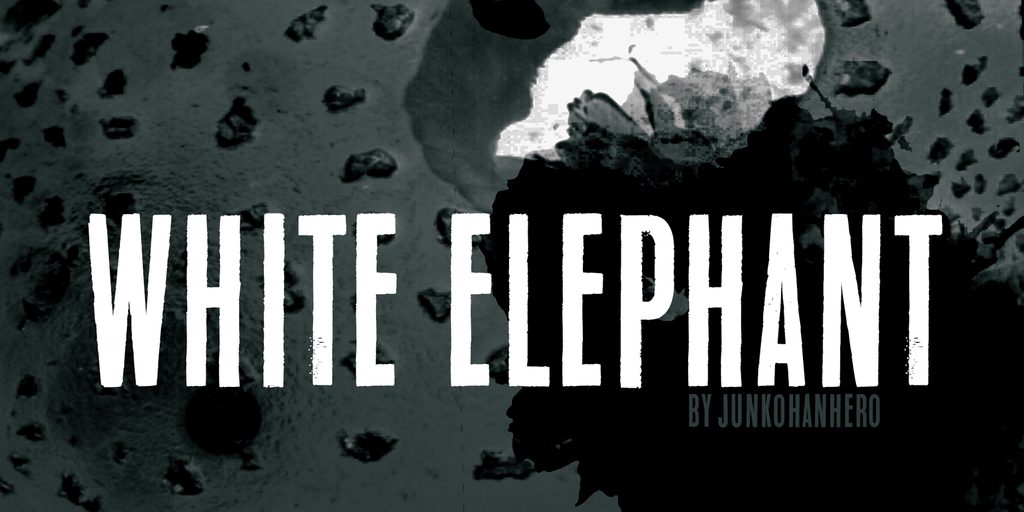
White Elephant Font – Fonte Grátis
White Elephant Font
A fonte “White Elephant” foi criada pelo designer Hamilton para quem busca uma fonte retro e moderna no mesmo tempo. Com seus traços agradavelmente desproporcionados, esta fonte traz um toque vintage ao seu design contemporâneo. Perfeita tanto para projetos pessoais quanto para aplicações comerciais, “White Elephant” oferece a você uma maneira única de personalizar sua identidade visual. Seu uso em projetos comerciais requer uma licença comercial. Você pode adquiri-la comprando-a diretamente da Hamilton por meio do PayPal, pagando um valor de 15€ (ou $20) por license. Após o pagamento, apenas precisa enviar um e-mail para Hamilton com os detalhes solicitados. Além disso, você também tem a opção de usar um botão de doação próximo ao botão de download. Nesta categoria de fontes retro, “White Elephant” é uma opção que não decepciona. Combinando elementos das fontes vintage clássicas com a agilidade e personalização moderna, esta fonte pode ser a chave para dar um toque único ao seu design.